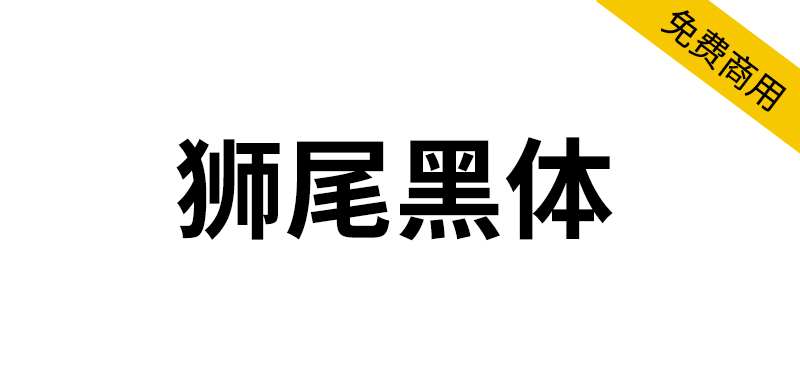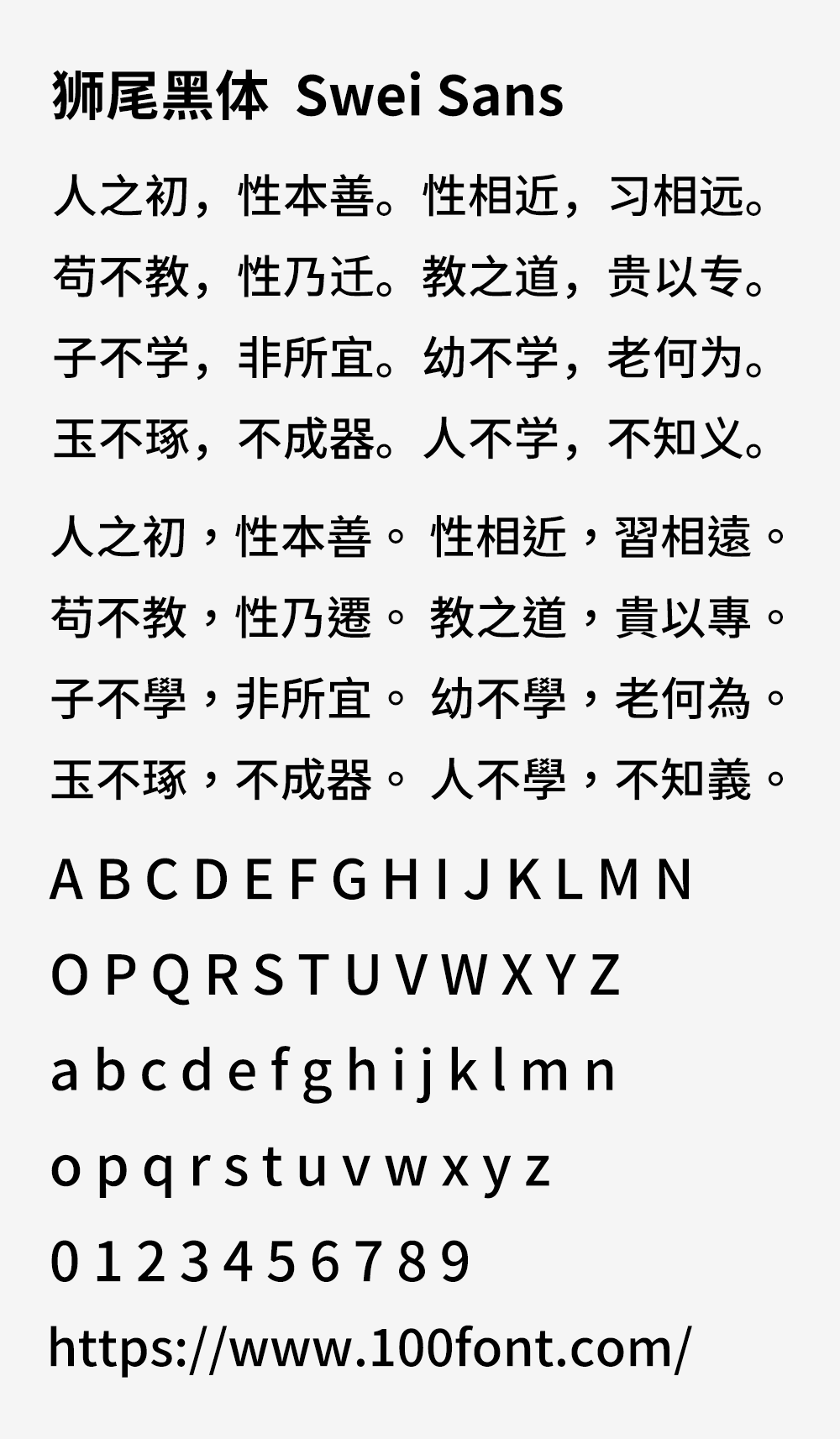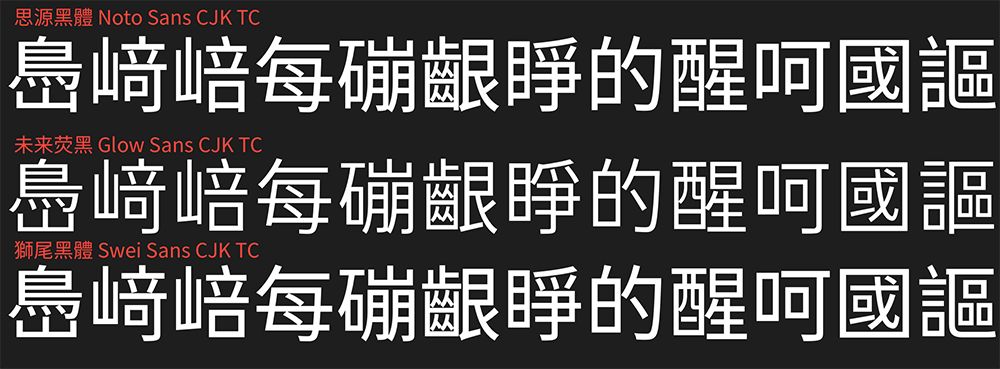
狮尾黑体基于思源黑体的拔脚改造,更加简明现代化的字体,支持简体中文、繁体中文、韩文与日文,提供给大家改造后的思源黑体7种字重。
狮尾黑体和「思源黑体」差别在有没有拔脚,「拔脚」就是会有较少的笔画,例如移除「口」字的左右下角会多出的短线条。有拔脚的字会较圆,但是会造成有些字因直接去掉腿后左右不平衡、左右不对衬的「悬空」问题。
相比于思源黑体,狮尾黑体的造型更加简明现代,版面效果清新轻快,在较重的字重里,有些脚很难判断该不该拔,就留着了,以避免误拔。